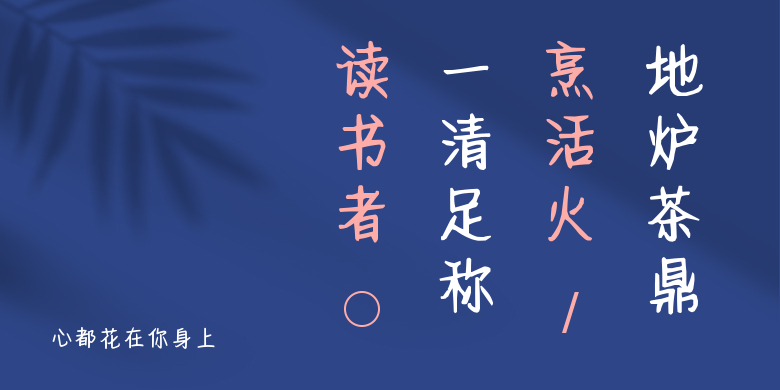
心都花在你身上
心都花在你身上,这款字体结构工整、笔画清晰,兼顾美观与易读性,适用于标题、正文、海报、包装、LOGO 等多种场景。字形优雅稳定,风格百搭耐看,适配日常排版与创意设计,让文字呈现更舒适、更具质感。心都花在你身上一笔一画,皆是细节,以均衡的比例、流畅的线条打造舒适视觉体验,字形端正大气,风格简约现代。无论是商业设计、品牌宣传还是日常排版,都能轻松驾驭,让文字更有格调与力量。心都花在你身上字体下载。